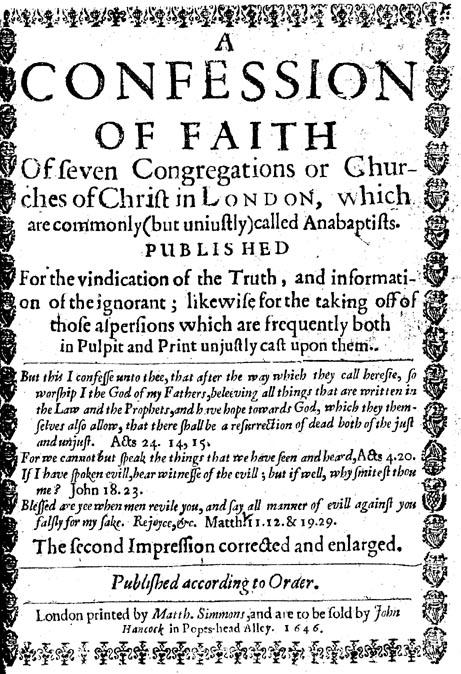
Titelblatt von 1646 (Londoner Bekenntnis)
Welche Schrift ist das? ;-)
Ich rechne jetzt eher nicht mit einem Font der letzten Jahre. Auch nicht Jahrzehnte.
Es geht darum, dass eine Übersetzung des Bekenntnistextes veröffentlicht werden soll (erstmal ganz schlicht als .pdf zum kostenlosen Download), und ich würde gern eine Schrift wählen, die in die Richtung, die allgemeine Anmutung der damals benutzten geht.
Ich will ganz klar nicht den Eindruck des historischen Satzes von damals wiedergeben, nur überlege ich, die zu nutzende Schrift nach der des Originals auszuwählen.
Was denkt Ihr, in welche Richtung könnte man da gehen?
Für die zunächst angedachte Verteilung als .pdf: "sauber" - die Zielgruppe wüsste Anderes m.E. mehrheitlich nicht zu würdigen und ginge wohl eher davon aus, dass schlampig gearbeitet wurde.
An die historisierende Möglichkeit hatte ich auch schon gedacht und finde sie sehr reizvoll, ist aber erstmal nicht dran.
Garamond, evtl. in Form der Cormorant, war auch mein erster Gedanke, aber ich wollte eine zweite (dritte, vierte...) Meinung einholen.
Edit: Für einen historisierenden Nachsatz hätte ich mir wohl die Fell Types (http://iginomarini.com/fell/) näher angesehen...
Ich bekenne: Nein. :-(
Der Text soll gelesen, verstanden und im aktuellen Kontext diskutiert werden, da will ich dem Leser nicht im Wege stehen.
Aber es schmerzt mich in der Tat. Wie gesagt, vielleicht später mal ein historisierender Satz...
Steht zu befürchten, obwohl ich sie liebe. Ich versuche mich mal an einer entsprechenden Gestaltung, und stelle sie dann zur Diskussion.
Richtig, wobei nahe kommt in die Richtung stilistisch nahe kommt zu interpretieren ist.
Ich wollte hier primär meine Einschätzung, dass die Garamond-Richtung nicht so falsch ist, überprüft haben (ist oben durch Norbert geschehen) und werde jetzt eine erste Gestaltung auf Basis der Cormorant medium versuchen. Für den Fall, dass das nicht klappt, und wenn jemand spontan eine Alternative einfällt, freue ich mich, wenn er sie nennt.
EB Garamond 08? Wäre jetzt zumindest erstmal einer meiner Favoriten bei den Rahmenbedingungen und der Vorlage …
Will ich mir gern mal wieder anschauen, danke. An der EB Garamond schreckt mich immer ab, dass Georg Duffner selbst das Projekt als sehr unfertig eingestuft hat, aber sich seit Mitte 2014 auch nichts mehr getan hat.
Und an der Cormorant locken mich die immensen Möglichkeiten (Infant-Schnitt für Anmerkungen (etwa Fußnoten), yeah!), wobei ich schon auch befürchte, dass sie zu filigran ist.
Edit: Ich merke gerade, dass ich zumindest die Option für ein ziemliches Missverständnis offengelassen habe: Ich will nicht dieses Titelblatt nachsetzen, sondern eine Übersetzung des (hier nicht wiedergegebenen) Inhalts dieses Büchleins veröffentlichen.
An der EB Garamond schreckt mich immer ab, dass Georg Duffner selbst das Projekt als sehr unfertig eingestuft hat
Ich glaube, dass er sich da auf  nie so ganz fertig gewordenen Zusatzkram wie die Initialen oder andere Zierelemente bezieht. Bei den Textschnitten habe ich eigentlich nie irgendwelche Probleme gesehen. Probier’s doch einfach selbst aus:
EB Garamond
EB Garamond 08
EB Garamond 08 Italic
N.b. Der Schriftmustergenerator, der die obigen Beispiele erzeugt hat, hat bei vielen Schriften leider Probleme mit dem Kerning. Das sollte im Druck besser sein.
So, im ausgeprägten Bewusstsein meiner Unzulänglichkeit habe ich mal einen ersten Versuch erstellt.
Vorab: Die Datei soll im Netz verfügbar gemacht werden, muss also am Bildschirm vernünftig darstellbar sein. Daneben ist davon auszugehen, dass Leser sie auch ausdrucken werden, und über die Parameter dieses Druckes lässt sich natürlich wenig vorhersagen - nicht einmal, ob ein- oder zweiseitiger Druck erfolgt. Das habe ich versucht, bei der Gestaltung zu berücksichtigen.
@Þorsten: Ich haben erstmal nicht die EB Garamond, sondern die Cormorant gewählt.
4. Der „ursprüngliche Titel“ (also der ganze kursive Text auf Seite 3) wirkt für mein Gefühl etwas unpassend, ich würde ihm entweder eine  separate Seite geben, oder ihn mit auf die vorangegangene Seite stellen.
Steht die Adobe Garamond Pro zur Verfügung?
Es stehen alle freien Schriften zur Verfügung, darunter die URW Garamond No 8 aus dem Ghostscript-Paket, die EB Garamond und die Cormorant.